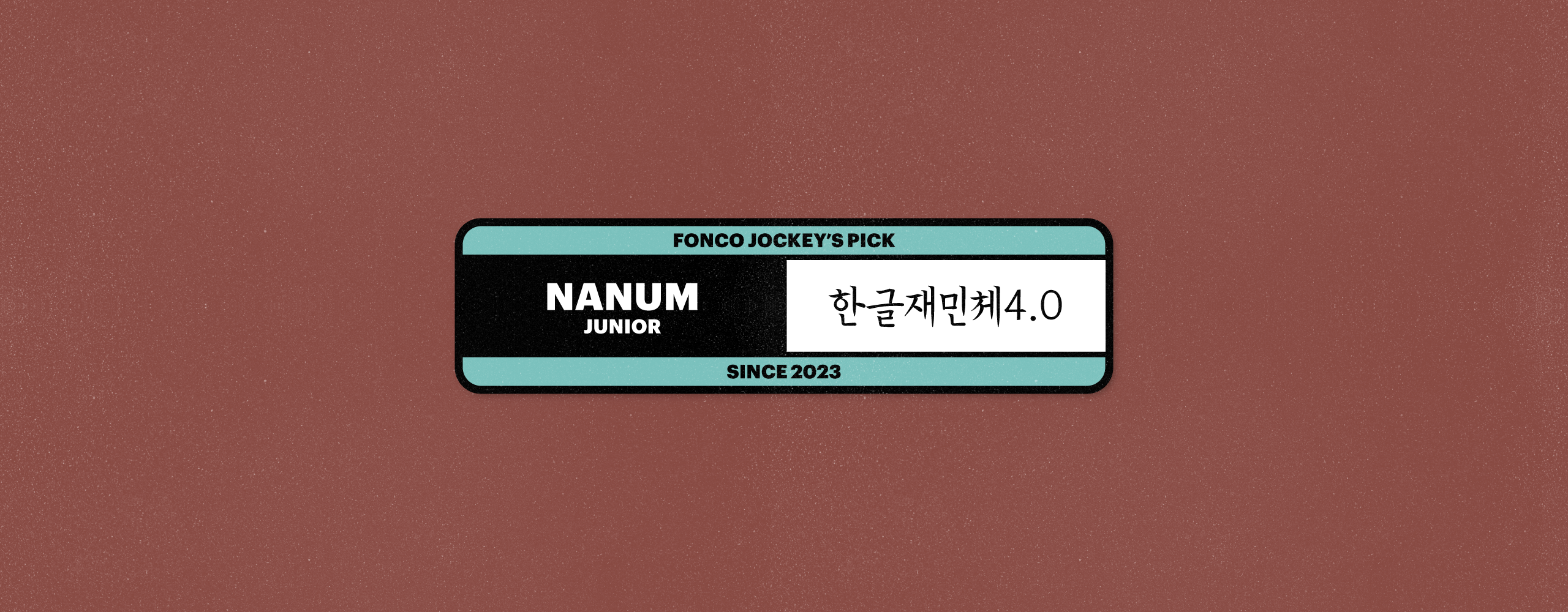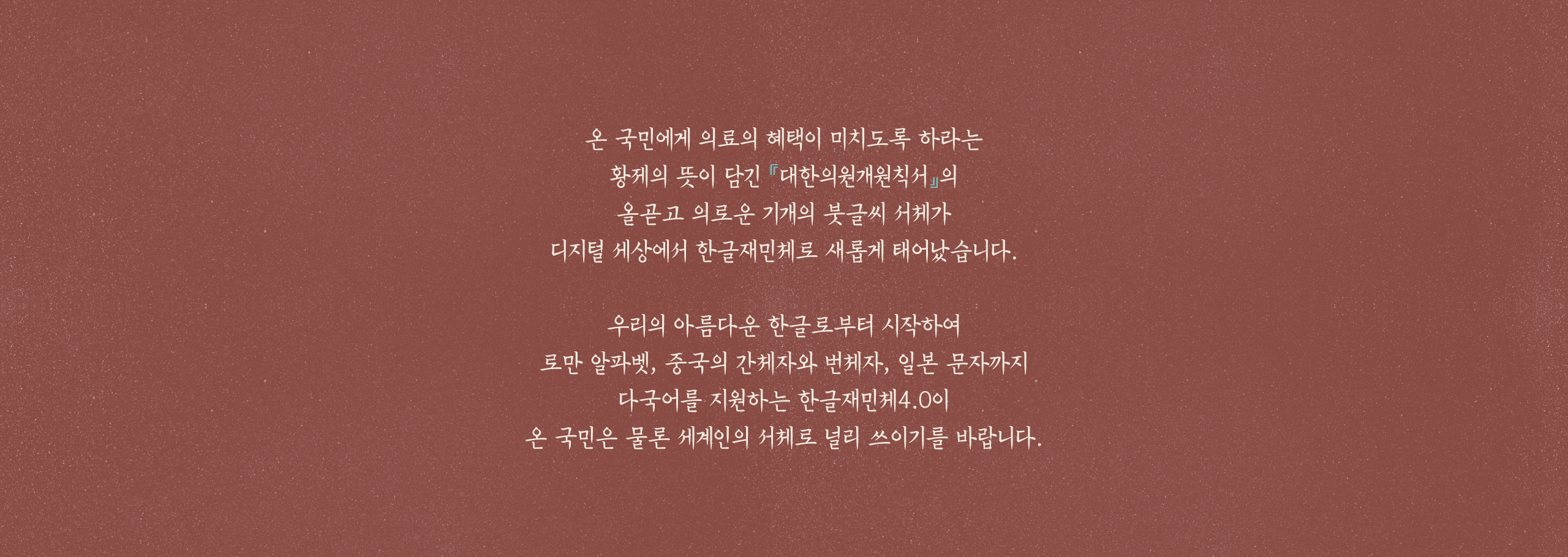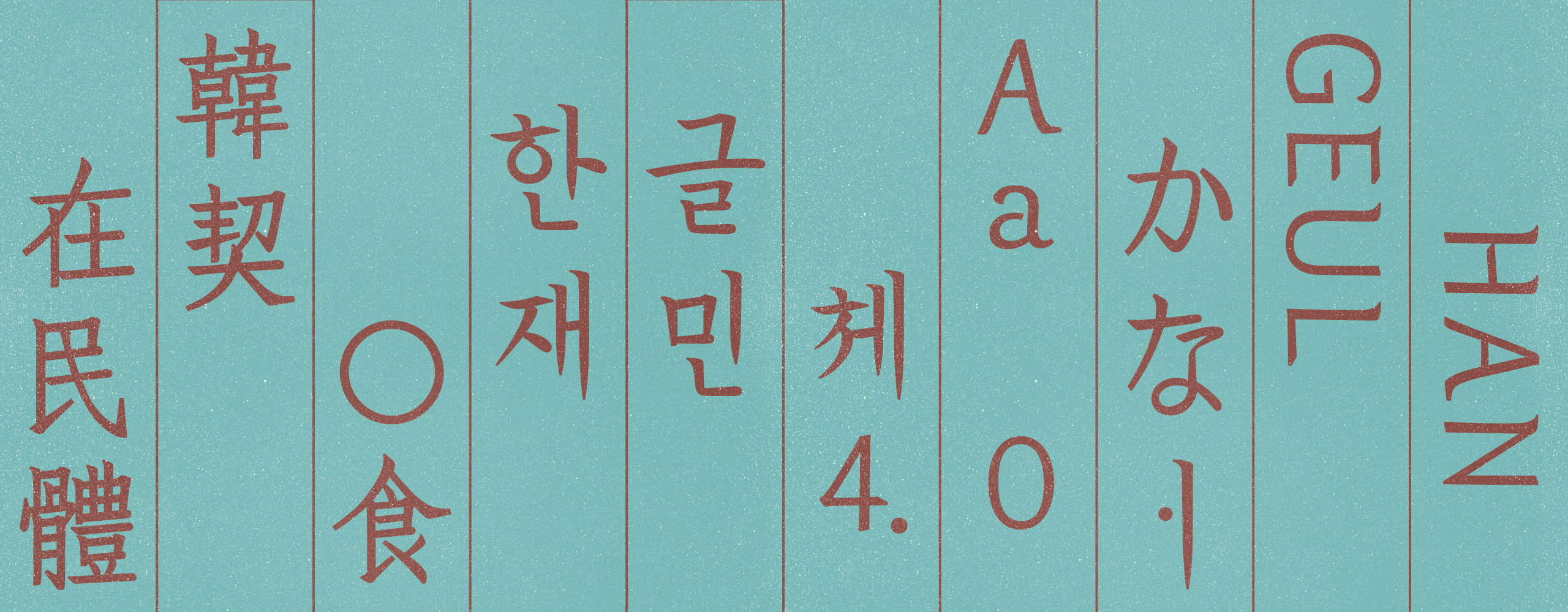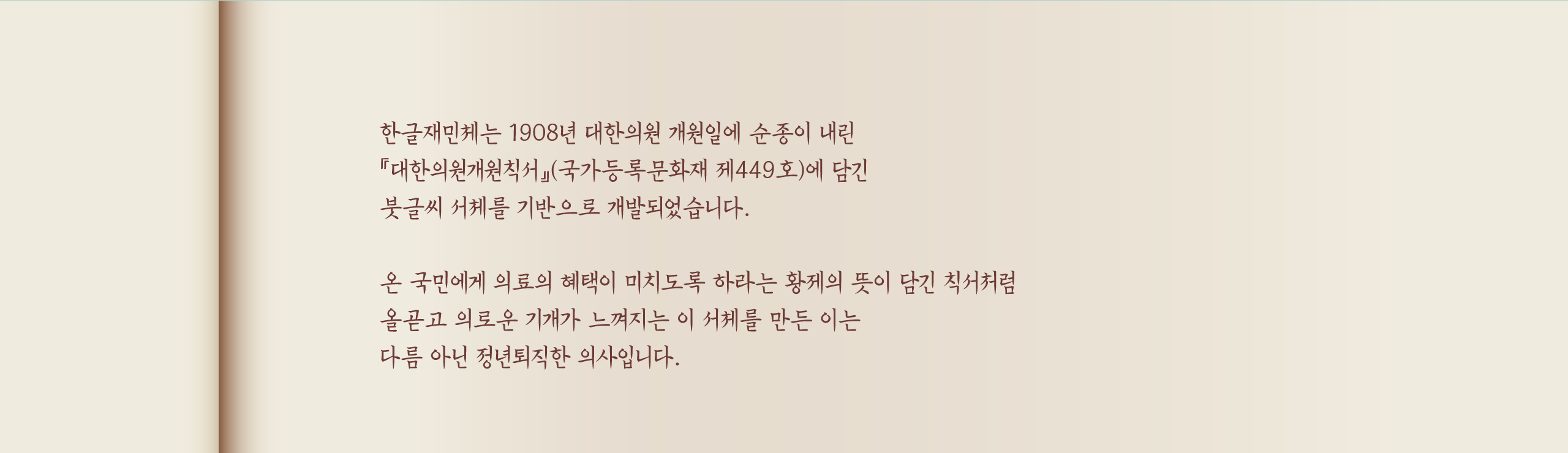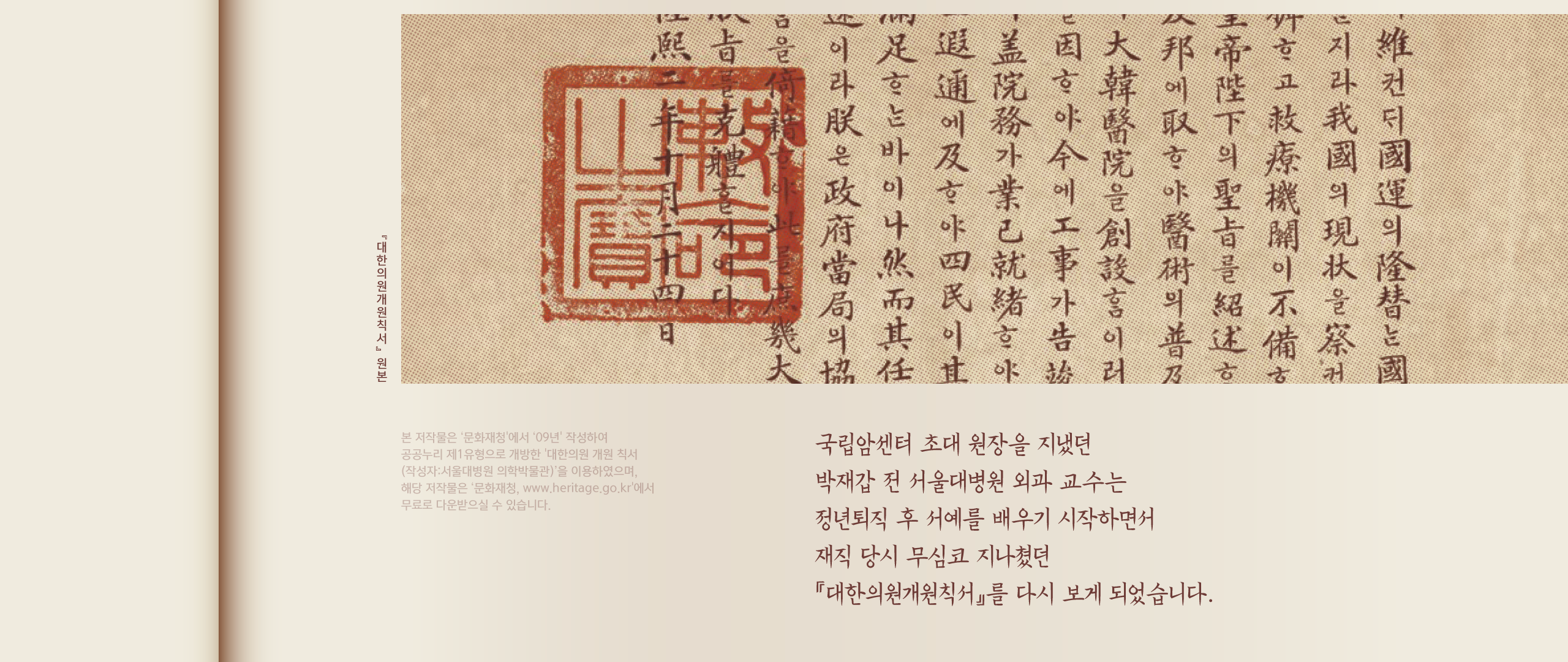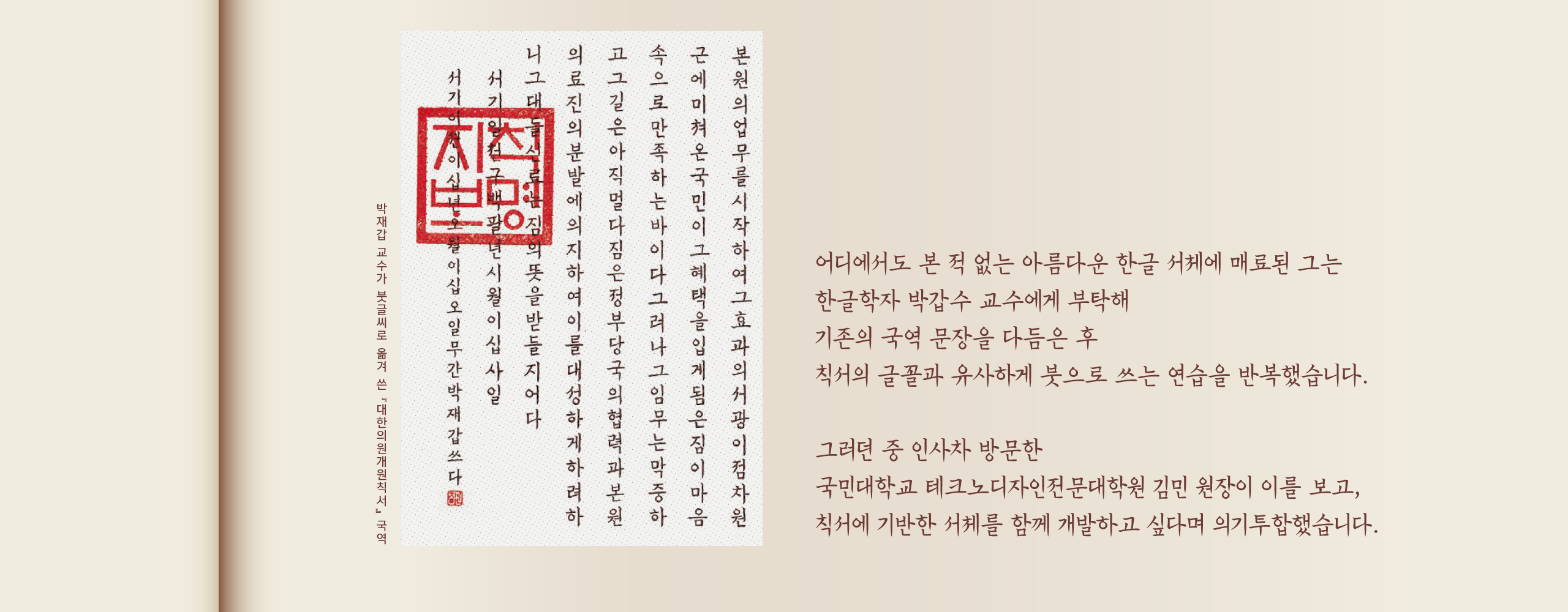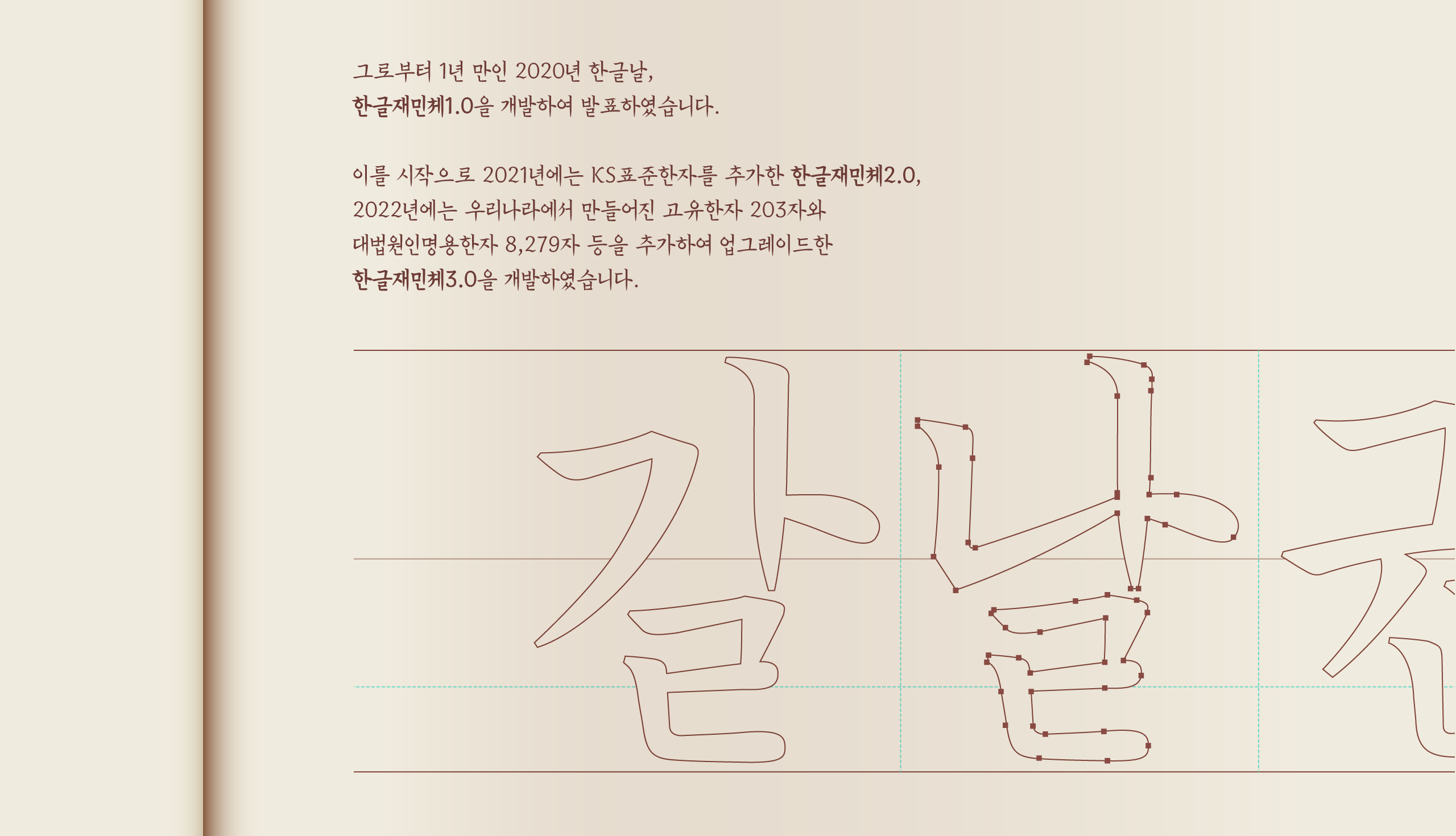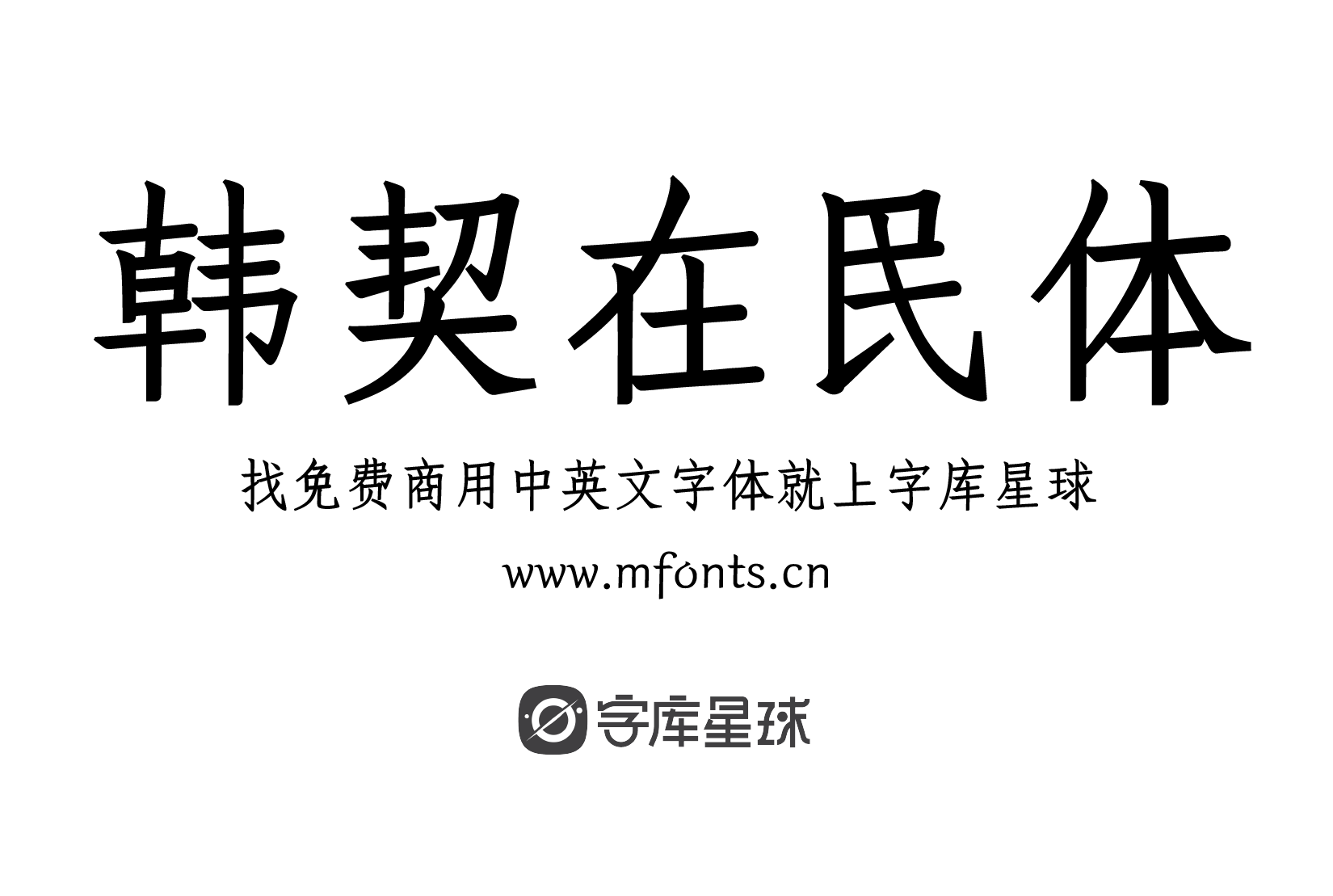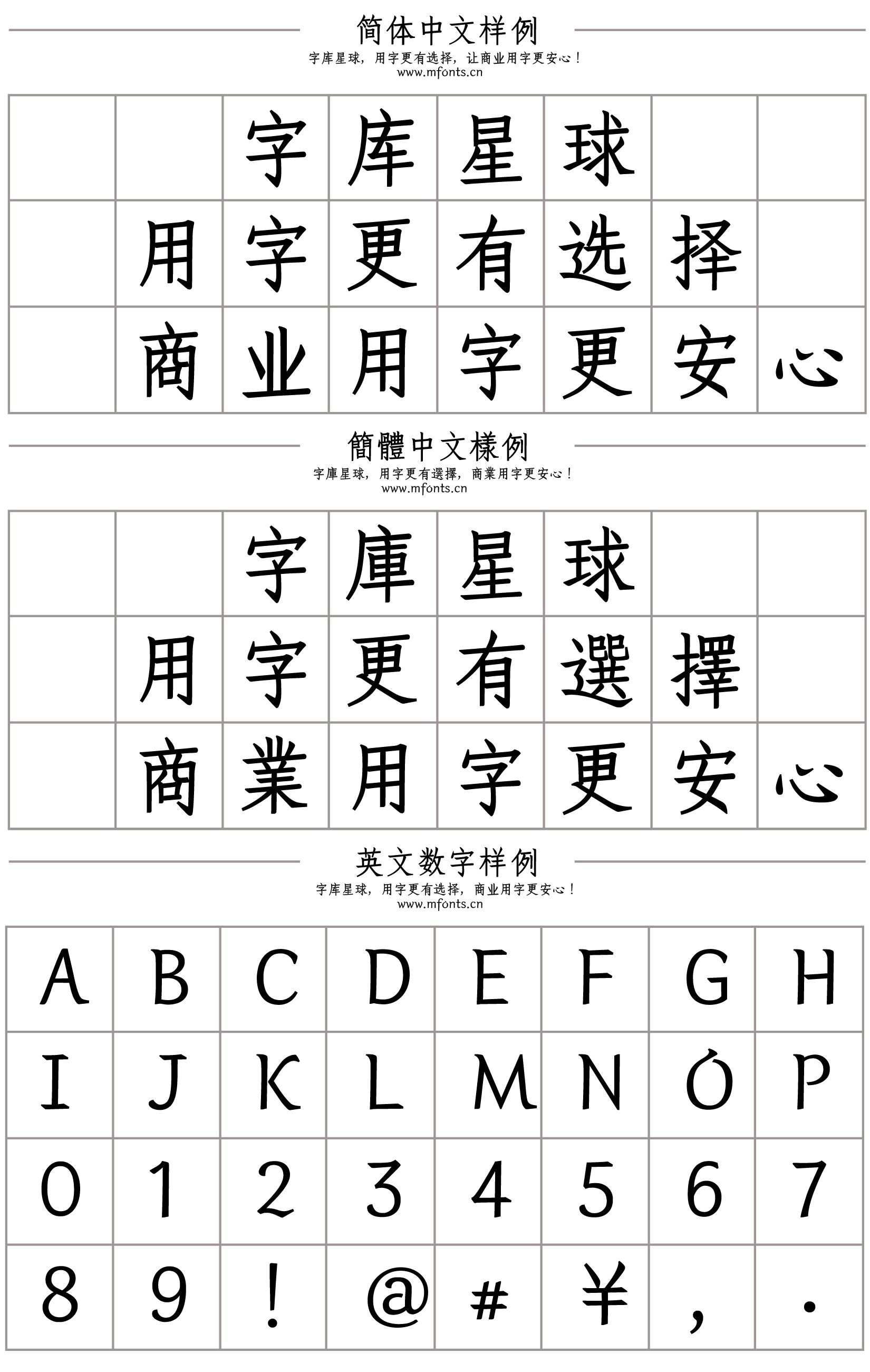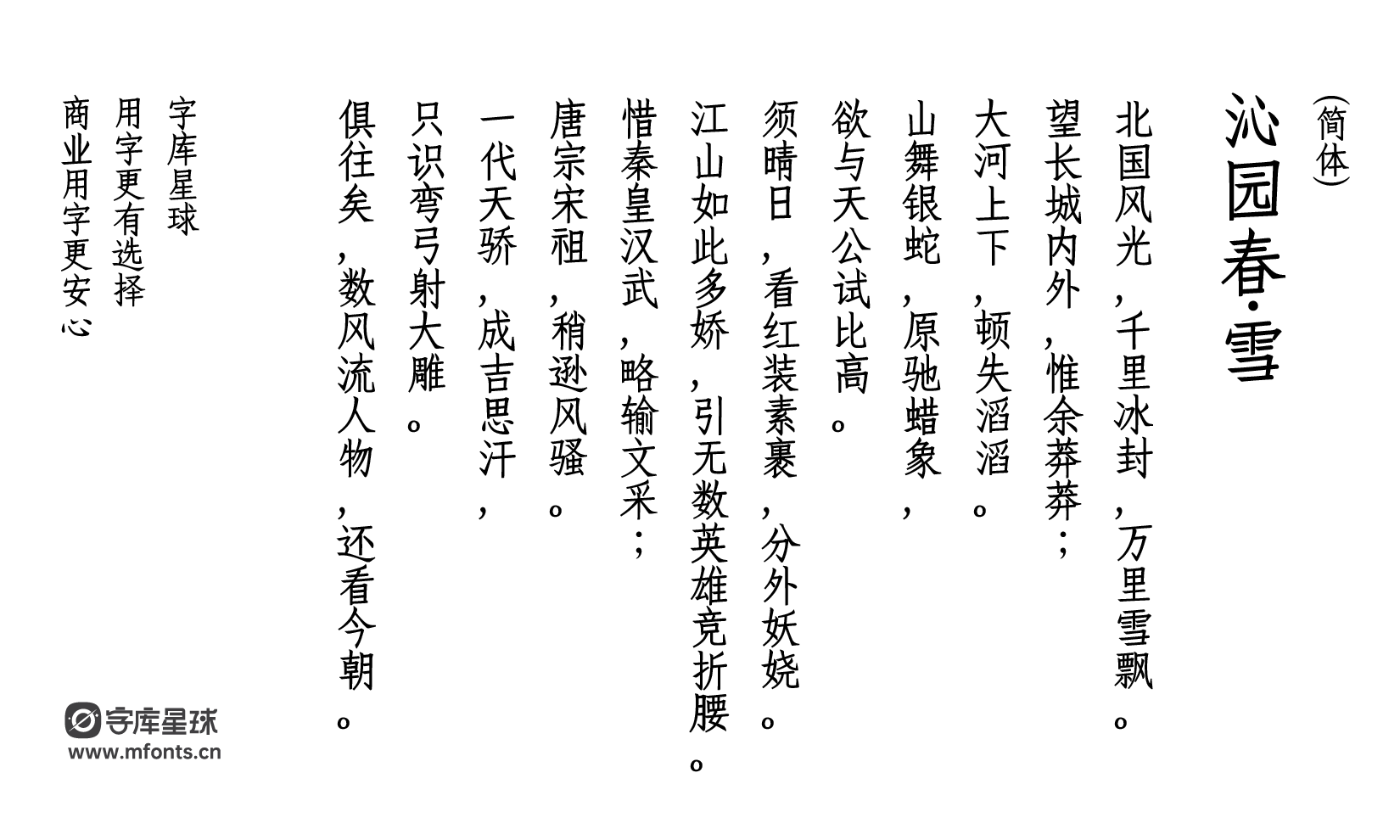
韩契在民体(韩文名:한글재민체,英文名:hangeul jaemin)是以1908年颁布的《大韩国会开幕原则书》(国家注册文化财第449号)中的毛笔书法字体为基础,由朴载甲前首尔大学医学院教授和金敏国民大学技术设计专门大学院院长共同开发。2020年在韩文字日发布了韩契在民体1.0,2021年增加了KS标准汉字的韩契在民体2.0,2022年又增加了韩国独有的203个汉字和大法院人名用8289个汉字等,发布了升级版的韩契在民体3.0。而由尹设计集团(윤디자인그룹)于2023年发布的韩契在民体4.0,增加了中国人日常使用的标准简体字和繁体字、日本汉字以及平假名和片假名等。至此,韩文和拉丁字母、中国简体字和繁体字、日本文字也由相同的设计组成,完成了支持多种语言的数字字体。